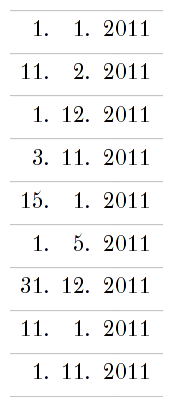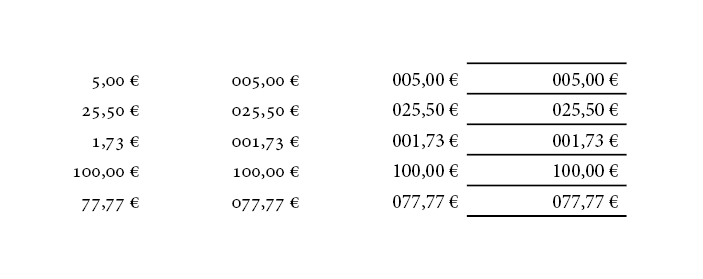
einer Zahl eine Null voranstellen
Da fehlen ja auch immer noch die Abstände zwischen Tag / Monat und Monat / Jahr.
Die würden das Unglück nur noch vergrößern. Beitrage (poste soll ich ja nicht sagen) doch bitte mal ein Bild wie du dir in einer Tabelle ohne führende Null vorstellst … :-)
Dann würde ich doch mal vorschlagen: trete Du doch den Gegenbeweis an und zeige uns wie man es richtig macht!
Einfach nur zu behaupten daß das auch ohne die 0 übersichtlich ginge nützt überhaupt nichts. Aus meiner Daten-Erfahrung kann ich jedenfalls bertel nur Zustimmen, daß Daten in tabellarischer Form oftmals mit der 0 übersichtlicher dargestellt werden können. Jetzt dürfen alle, die anderer Meinung sind, gerne zum Gegenschlag blasen. Aber bitte mit Beispielen und nicht nur vage in den Raum hinein. :twisted:
Ich kann bertel nur zustimmen, eine führende 0 ist wesendlich besser zu lesen als ohne, mal zu schweigen von den komischen Zwischenräumen.
Im Fließtest ist das was anderes da macht es einfach keinen Sinn, aber in der Tabelle …
Man kann natürlich das Ganze soweit auseinander ziehen, dass Tag - Monat - Jahr quasi komplett für sich alleine stehen. Bliebe aber die Frage wie schnell man dann die Daten erfassen kann (Leserfreundlichkeit).
Die Leerzeichen sind nicht DIN-5008-konform, daher ist dein Beispiel zwar hübsch, aber schwer erfassbar und irrelevant.
… daher ist dein Beispiel zwar hübsch …
Hübsch? Ich bin wahrlich kein Freund der Nullen, aber die Daten sind doch völlig zerrissen und damit alles Andere als hübsch. Vom Regen in die Traufe, würde ich sagen. :bandit:
Pachulke, ich bin auf Deiner Seite! :-D
Ja, so hatte ich das gedacht, habe im Moment hier viele Baustellen gleichzeitig und konnte es nicht selbst illustrieren. Natürlich könnte man die Abstände noch etwas verringern, um dem Eindruck der Zerrissenheit entgegenzuwirken.
Hübsch? Ich bin wahrlich kein Freund der Nullen, aber die Daten sind doch völlig zerrissen und damit alles Andere als hübsch. Vom Regen in die Traufe, würde ich sagen. :bandit:
Ich hatte den Ironie-Smiley vergessen, verzeih’ ;-) Natürlich ist nicht hübsch. :gimmifive:
Dann würde ich doch mal vorschlagen: trete Du doch den Gegenbeweis an und zeige uns wie man es richtig macht!
Ich finde, dass Bertels eigenes Beispielbild das recht gut zeigt. Oder sollte das tatsächlich nur mir so gehen? Die rechte Spalte ist zwar in dem Sinne aufgeräumter, dass sie gleichförmig aussieht, aber ein Datum heraussuchen ist doch eindeutig in der linken Spalte leichter und angenehmer, gerade dadurch dass sie nicht so einheitlich ist ...? Rechts hat das Auge ja gar nichts, an dem es sich irgendwie festhalten kann, während es die Zeilen hinabfährt :-?
Ähnlich bei Daten die keine Kalenderdaten sind, ich hab mal das Spiel »Schraub Stück für Stück die Lesbarkeit der Tabelle herunter« gespielt:
Ganz links haben wir mediävale Tabellenziffern. Alles schön untereinander, kleine und große Werte auf den ersten Blick erfassbar, toll :-D Dann Nullen davor. Immer noch brauchbar, man kann zumindest die Zahlen gut lesen und hat noch Ankerpunkte für die Augen, aber die Größenunterschiede treten zurück. Dann Versalziffern mit Nullen, jetzt haben wir fast nur noch graue Balken gleicher Länge. Und dann noch so tolle Linien mit rein, und das Auge irrt über die Tabelle und wünscht sich was schönes zum kucken ...
Ich würde mich nicht so weit aus dem Fenster lehnen wollen und behaupten, dass diese zerstückelte Darstellung per se nicht funktionieren könnte, wenn die Leser darauf konditioniert werden.
Aber nach aktuellen (DIN-geprägten) Sehgewohnten im deutschsprachigen Raum ist das schlicht eine Katastrophe und funktioniert (in Tabellen!) nicht.
Es gibt eben Minuskelziffern und Tabellenziffern. Genauso gibt es Satzregeln, die sich für Fließtexte anbieten und solche, die in Tabellen besser funktionieren. Der krampfhafte Versuch die in Fließtexten unnötigen, führenden Nullen auch in Tabellen zu vermeiden, macht Meinung nach alles nur noch schlimmer. Man kann zwar dann der vertikalen Linie gut folgen und die einzelnen »Spalten-Werte« finden, aber das normale horizontale Lesen ist deutlich erschwert. Und darum geht es ja schließlich: das Datum selbst lesen zu können.
Edith: Geldbeträge sind ja wieder etwas völlig anderes! 005,00 Euro ist natürlich Käse.
Es gibt eben Minuskelziffern und Tabellenziffern.
:erstaunt kuck: Findest Du das jetzt echt ganz links nicht besser lesbar ...? :-o Mediävalziffern haben ja doch nicht nur den Vorteil, dass sie sich in einem Text besser zwischen die vielen Gemeinen einfügen, sondern sie teilen doch auch genau die Vorteile von Gemeinen gegenüber Versalien: dass sie dem Auge mehr Halt geben als Versalien ... :-?
… Ganz links haben wir mediävale Tabellenziffern. Alles schön untereinander, kleine und große Werte auf den ersten Blick erfassbar, toll :-D ...
Ich habe mal deinen Gedanken auf deine Tabelle übertragen und die Nullen, die keine Bedeutung haben, weggelassen. Wie du siehst, kommt da nichts Gutes raus …
Puh, bei Deinem Beispiel wird mir aber schwindelig … ;-)
Wenn ich in Briefen oder Rechnungen oder im Fließtext ein Datum schreibe (also überall da, wo es um Schönheit geht), dann hat das immer diese Form: 1. Monat 2011. Wenn ich aber ein Datum in einer schnöden Tabelle in eine reine Datumsspalte schreibe, in der es nicht um Schönheit geht sondern um die Nutzbarkeit, beispielsweise um die Sortierfunktion zu nutzen, dann verwende ich Führungsnullen. :-)